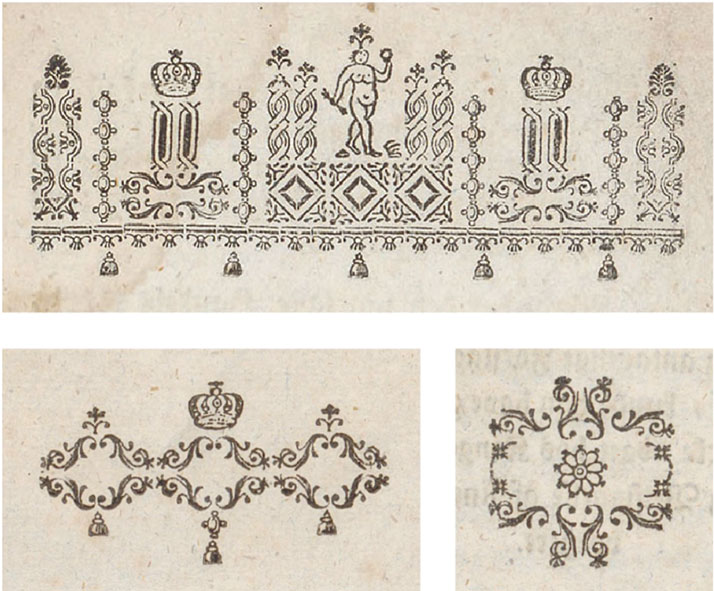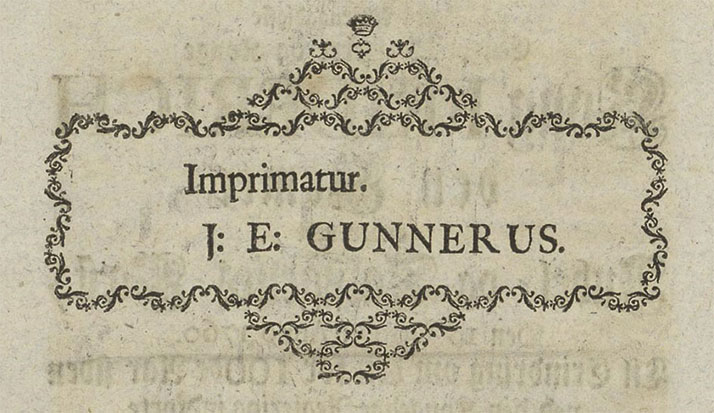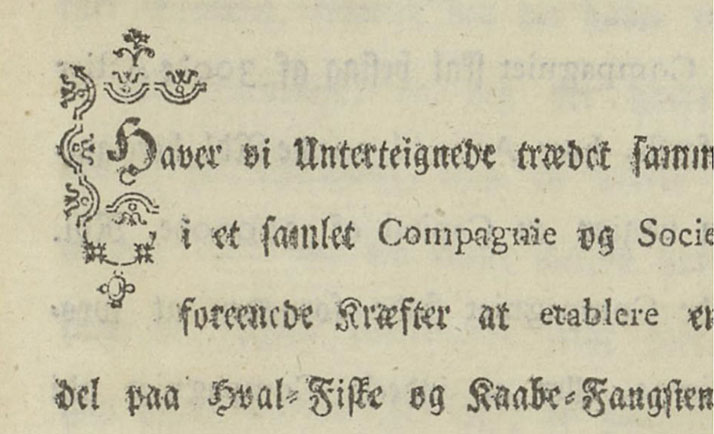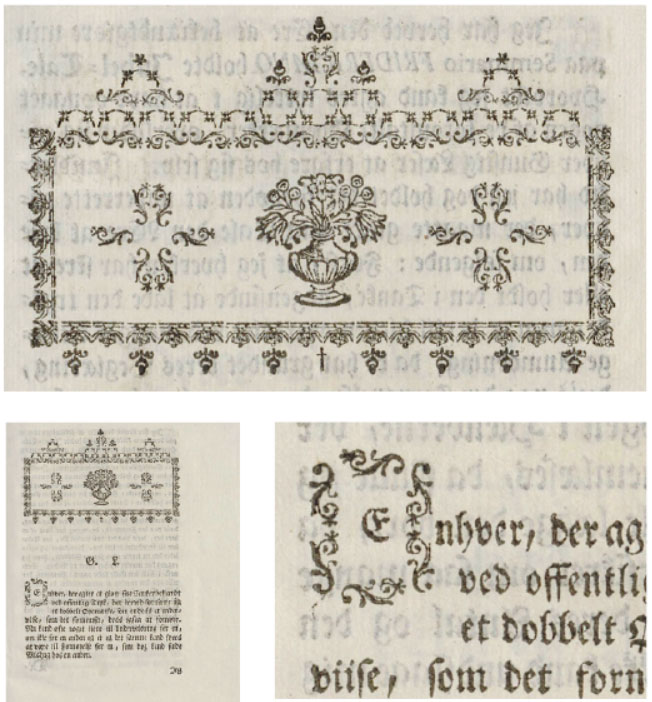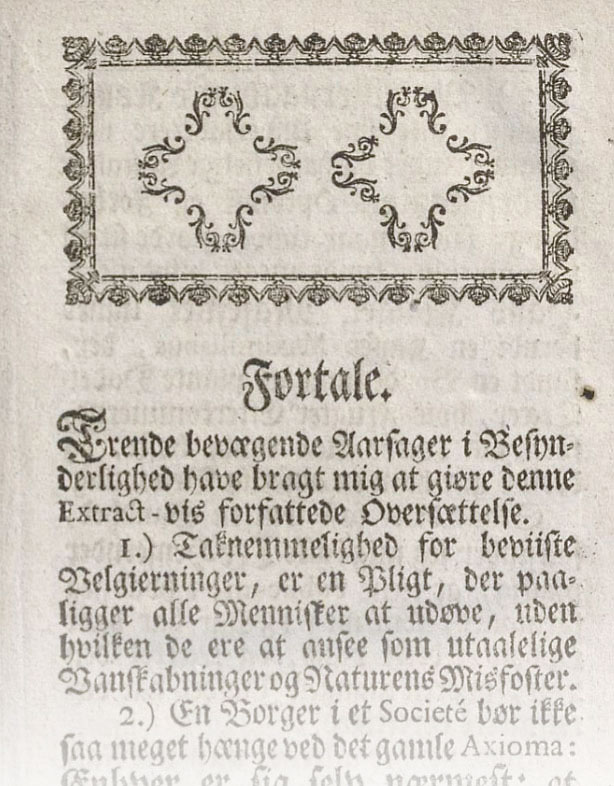
Rokokkoen gjorde seg gjeldende i norsk typografi i form av sjarmerende arrangementer av typografiske ornamenter. Boktrykkerne i Christiania, Bergen og Trondhjem fulgte den kontinentale stilutviklingen.
Rokokkostilen fant veien til norsk boktrykk i perioden 1750–1780. Boktrykkerne satte sammen små typografiske ornamenter til elegante arrangementer, indirekte inspirert av franske trykk.
Slike støpte ornamenter ble den gang i norsk og dansk typografi kalt røskener, fra tysk röschen (liten rose).1 De fleste er stiliserte motiver fra naturen, som eikenøtter, blomster, greiner og blader, andre er mytologiske figurer og symboler, eller har ikke-figurative og geometriske former.
Røskenarrangementet i Extract af det Kongel. Svenske Videnskabs Academiets Afhandlinger, trykt av Schwach i Christiania 1750, består av tre forskjellige røskener, som alle er vist i prøvearket til den danske kriftstøperen Pöetzsch. Dette er det tidligste arrangementet av røskener i rokokkostil som jeg har funnet i norsk boktrykk (Illustrasjon: Nasjonalbiblioteket)
Under den forutgående barokken ble røskener brukt til kraftige rammer rundt tekstsidene og til horisontale border, som markerte skiller i teksten. Da rokokkoen avløste den tunge barokken ble typografenes kunstneriske og tekniske evner stimulert til å sette sammen lyse og lette byggverk av røskener. Disse ble brukt som friser øverst på innledende sider, for innramming av begynnelsesbokstaver (initialer), som finaler (avsluttende ornamenter) eller rett og slett for å fylle tomrom på sidene.
Rokokkoen i typografien er nært knyttet til skriftstøperen Pierre-Simon Fournier – den mest kjente av flere berømte medlemmer av en stor boktrykkerslekt i Paris. For å skille ham fra de øvrige, kalles han også Fournier le jeune (den unge). I sin skriftprøve fra 1742, Modèles des caractères de l’imprimerie, viser han i tillegg til sine skrifttyper også «vignetter eller ornamenter i en ny stil, som ikke bare kan brukes alene, men som satt sammen til arrangementer [fr. desseins] kan utvides i det uendelige», som han skriver i den innledende teksten. I to plansjer viser han over hundre eksempler på dette.
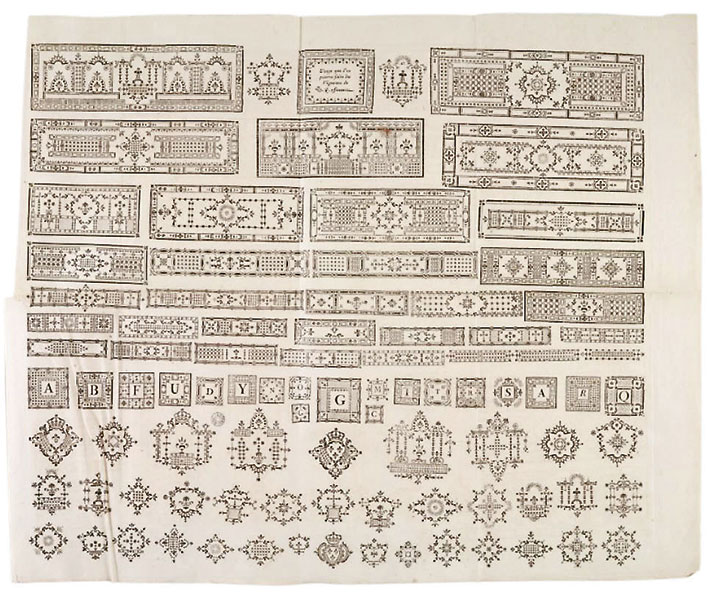
En av de to plansjene med Simon-Pierre Fourniers arrangementer av røskener i Modèles des caractères de l’imprimerie, 1742. Han vekslet ofte om på sitt fornavn, og er i dag mest kjent som Pierre-Simon. (Illustrasjon: Fournier 1742)
Fourniers eksempler på anvendelse av røskener i dekorative arrangementer ble ofte etterlignet i rokokkoperioden her til lands. De norske boktrykkerne fulgte den kontinentale stilutviklingen, selv om den tunge og mørke frakturskriften som dominerte her til lands ikke harmonerte like godt med rokokkoens lette eleganse, som antikvaskrifter gjorde.
Fournier skar også antikvaskrifter i rokokkostil, vist i hans seinere Manuel typographique fra 1764. Dette var blant de første forsirede skrifttyper noen sinne. Men disse kom ikke til Skandinavia før på 1800-tallet.
Det ser ikke ut til at Fourniers røskener, vist i hans 1742-prøve, havnet i norske settekasser. Dette var heller ikke nødvendig for å etterligne hans bruk av dem, for lignende røskener fantes i boktrykkeriene fra tidligere, og ble støpt av alle skriftstøperier. Men ved å støpe ornamentene på kegelstørrelser innenfor et helhetlig typografisk målesystem, var Fourniers røskener enklere å kombinere og ga bedre resultater, skriver skrifthistorikeren John Dreyfus.2
Det virkelig nye var rokokkoens anvendelse av røskener. Om ikke inspirert direkte av eksemplene i Fourniers skriftprøvebok, så har norske boktrykkere og deres kunder sikkert sett slike dekorative arrangementer av røskener i annen utenlandsk litteratur.
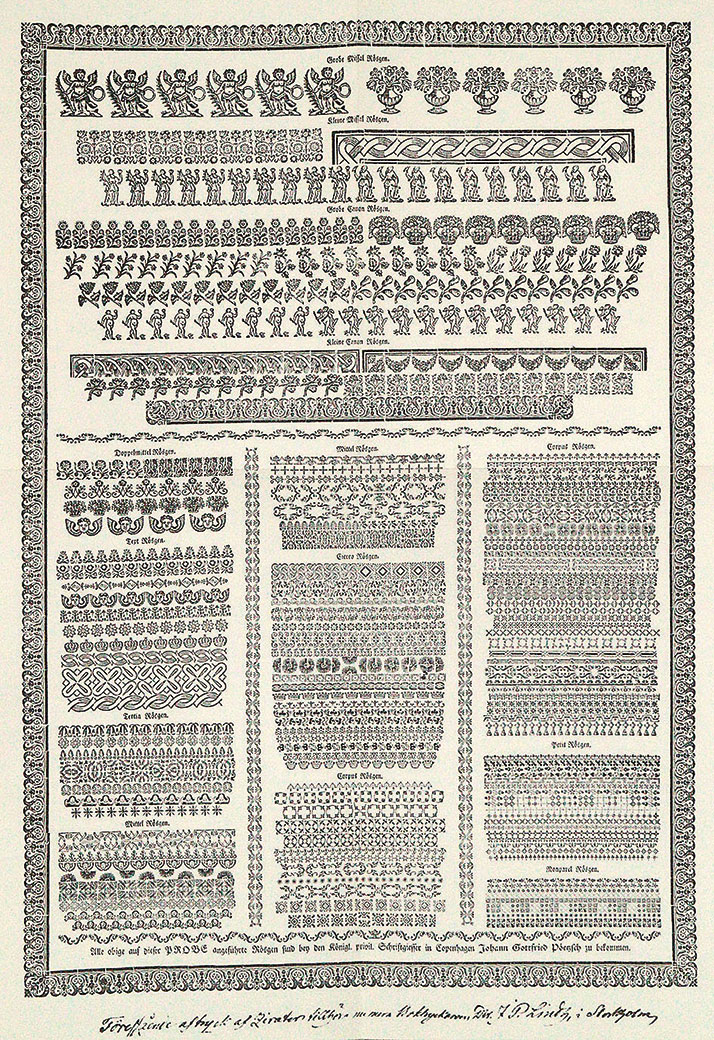
Skriftstøper Pöetzsch’ prøveark med røskener, ca. 1760. (Illustrasjon: Axel-Nilsson 1983)
Skriftstøperen Johann Gottfried Pöetzsch i København var leverandør av typer og ornamenter til norske boktrykkere i denne perioden; han hadde i praksis monopol på skriftstøping i tvillingriket Danmark-Norge midt på 1700-tallet.3 Han utga ca. 1760 tre prøveark; et av sine antikva- og kursivskrifter, et av sine fraktur- og schwabacherskrifter, og et av sine røskener. Ved å sammenligne sistnevnte med de norske boktrykkernes rokokkoarrangementer, ser man at mange av røskenene i disse med sikkerhet ble solgt av Pöetzsch.
Disse røskenene var neppe originale arbeider fra Pöetzsch’ side. Skriftstøperne og deres gravører solgte matriser (støpeformene) av sine typer og ornamenter til andre, som ikke sto i et konkurranseforhold til dem selv – altså utenfor nærområdet. Pöetzsch kjøpte matriser bl.a. fra Breitkopf i Leipzig. Boktrykker Johann Gottlob Immanuel Breitkopf kjente derfor til forholdene i København, og skrev i et brev til Pierre-Simon Fournier i 1763 at «Danmark har ingen gravør». Dette stemte riktignok ikke helt, for en liten del av Pöetzsch’ skrifter og ornamenter ble gravert i København.4
Det tidligste eksemplet jeg har funnet på et fullendt norsk rokokkoarrangement, er i Extract af det Kongel. Svenske Videnskabs Academiets Afhandlinger, trykt av Samuel Conrad Schwach i Christiania 1750. I de etterfølgende åra setter slike røskenarrangementer sitt preg på mange norske bøker, trolig der et elegant utseende var ønsket av utgiveren.